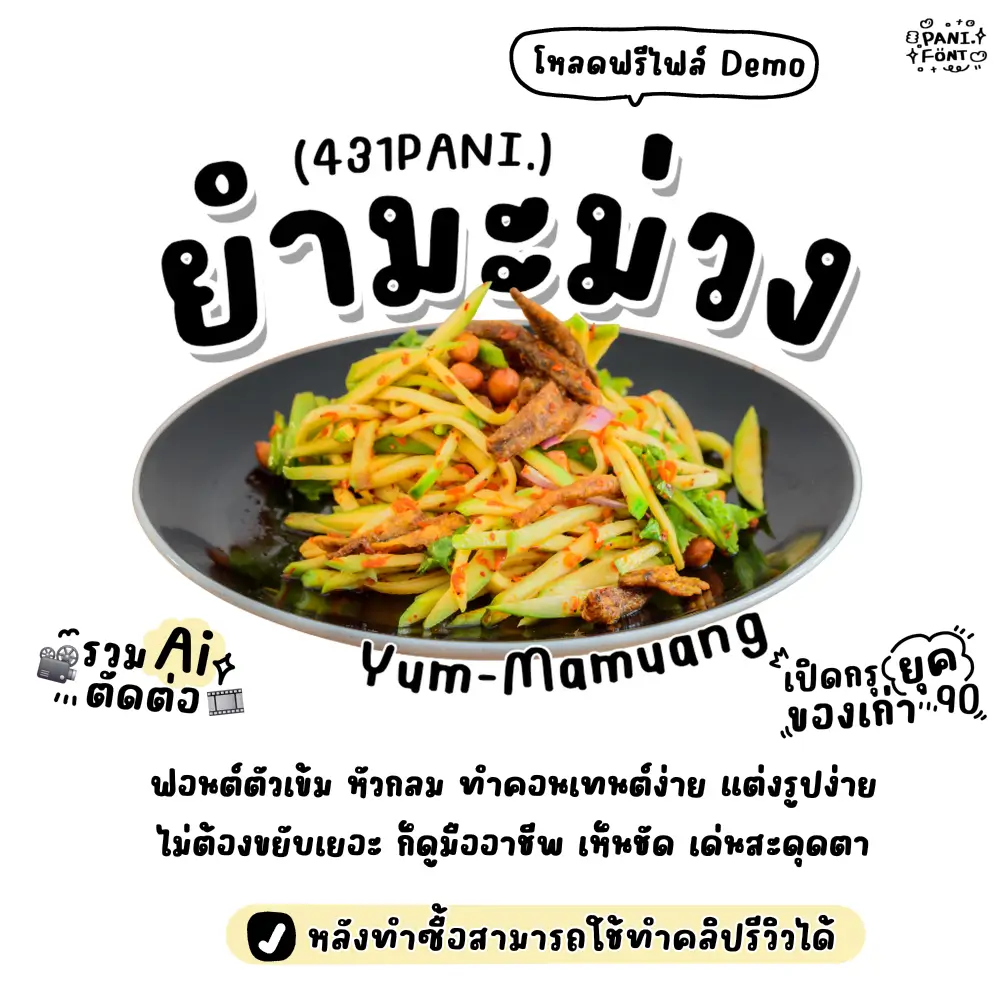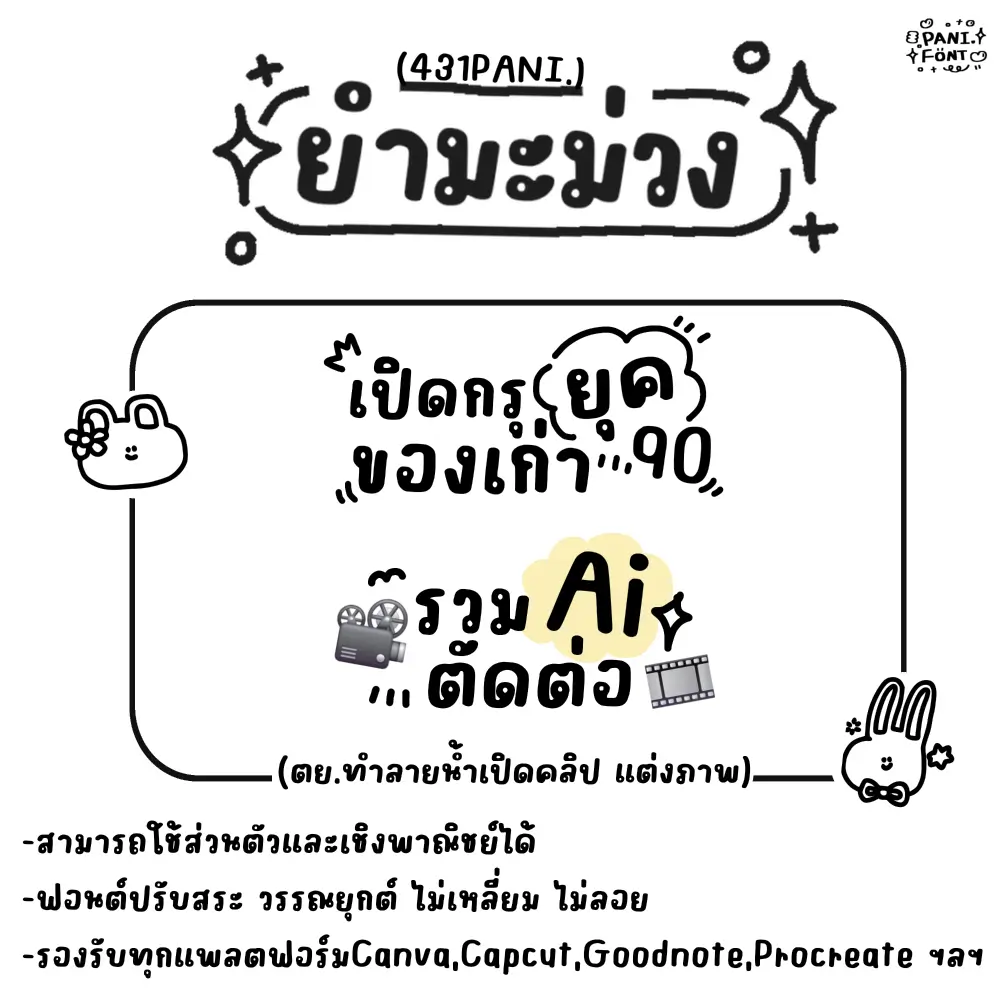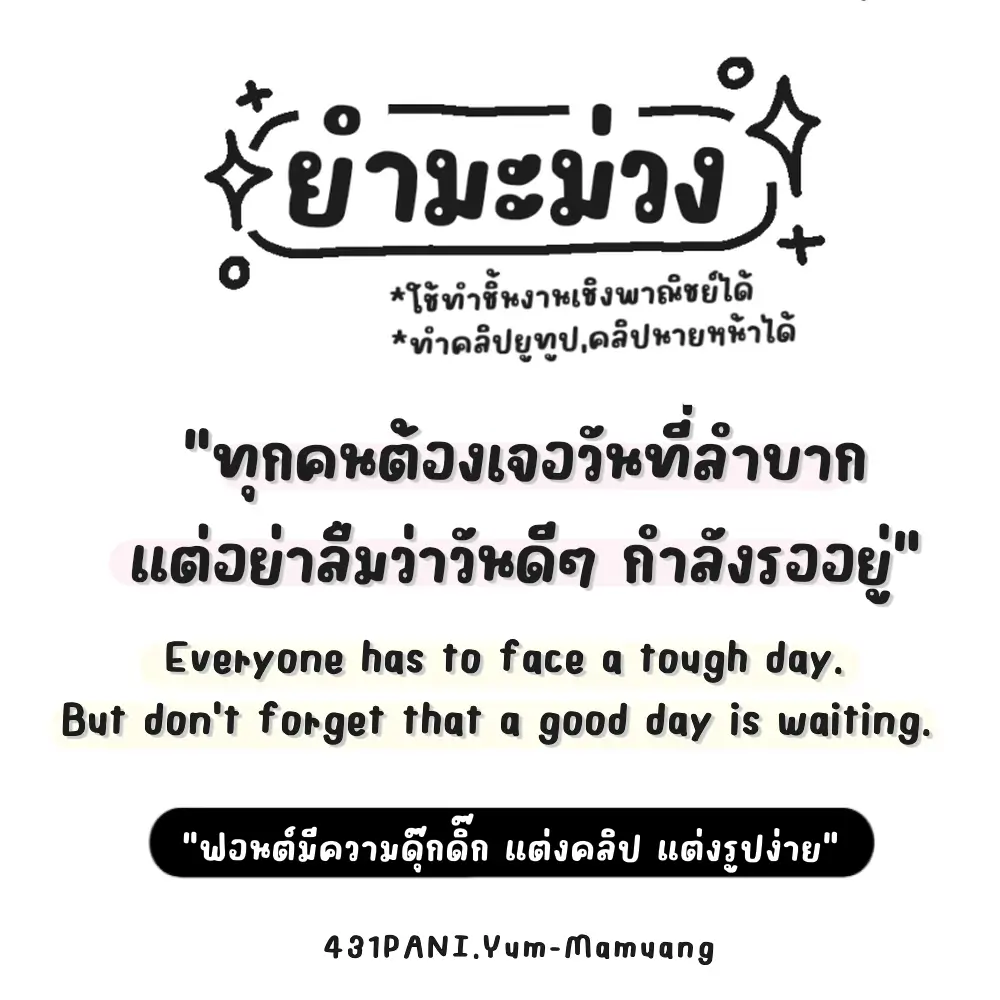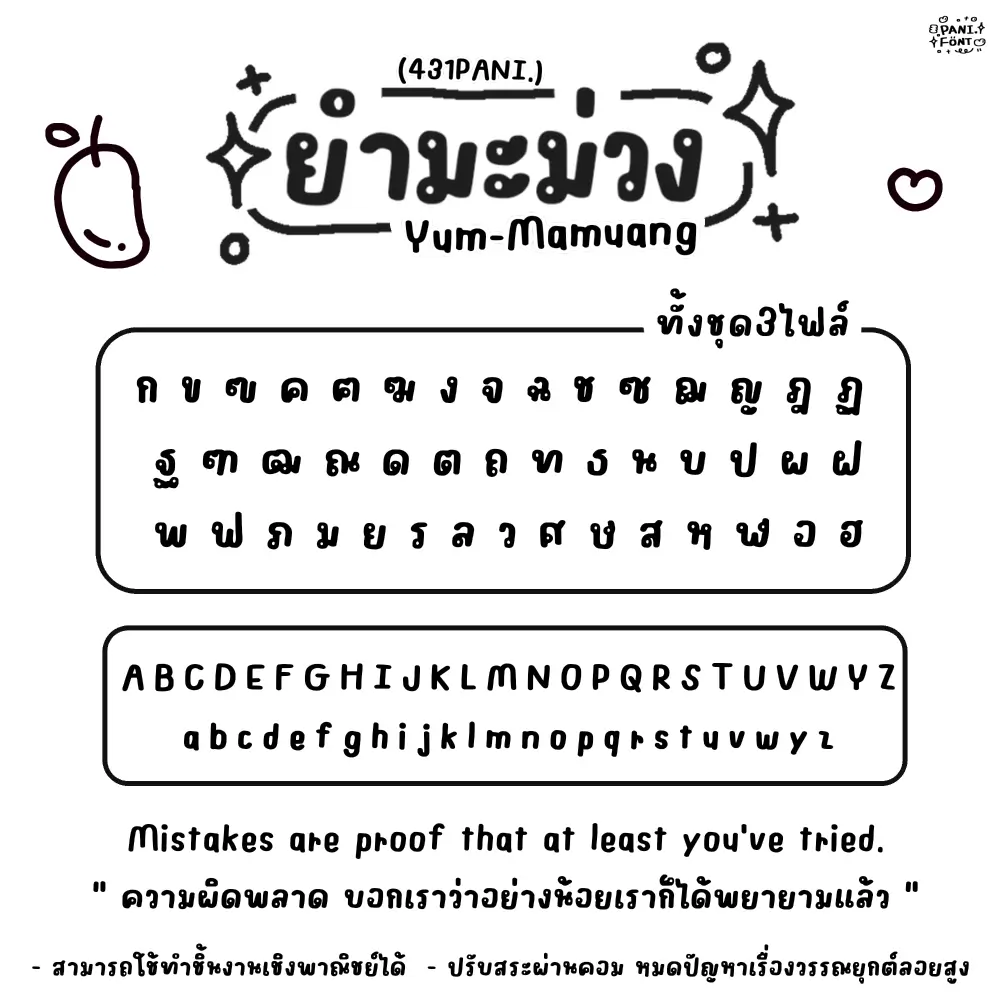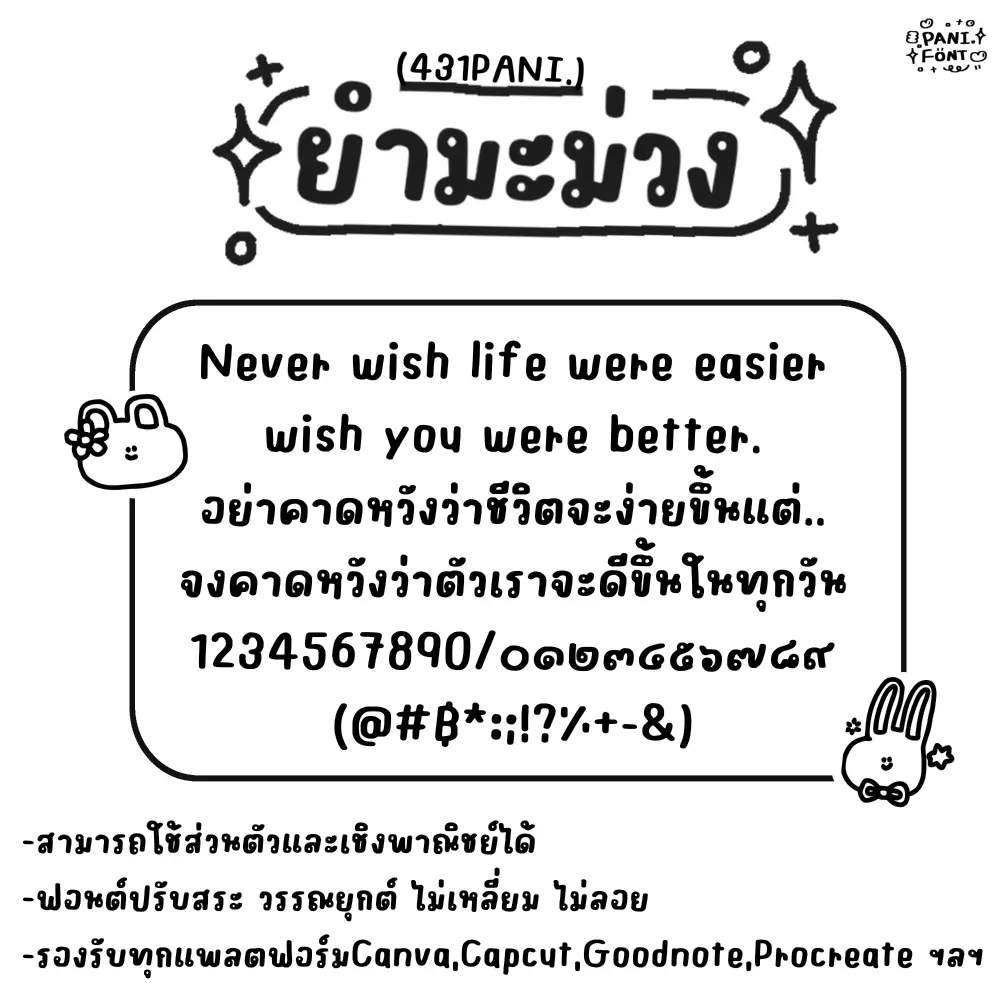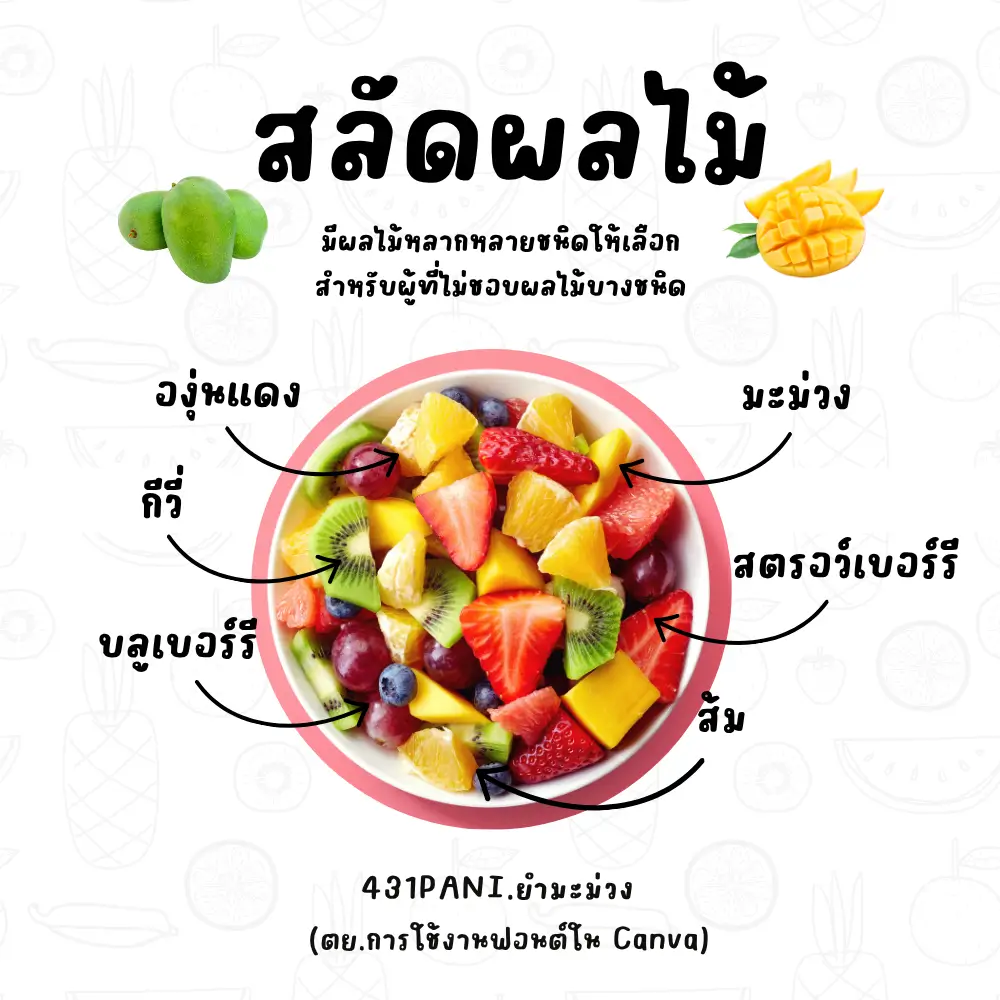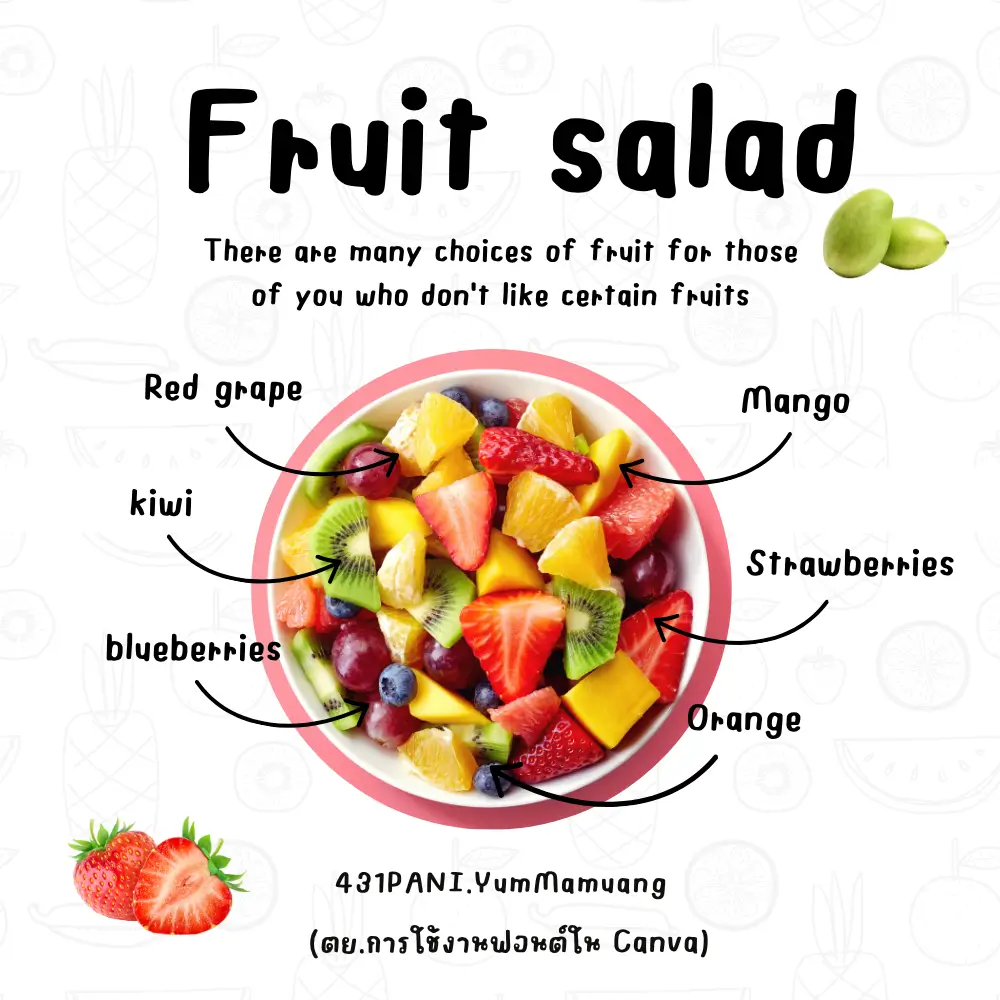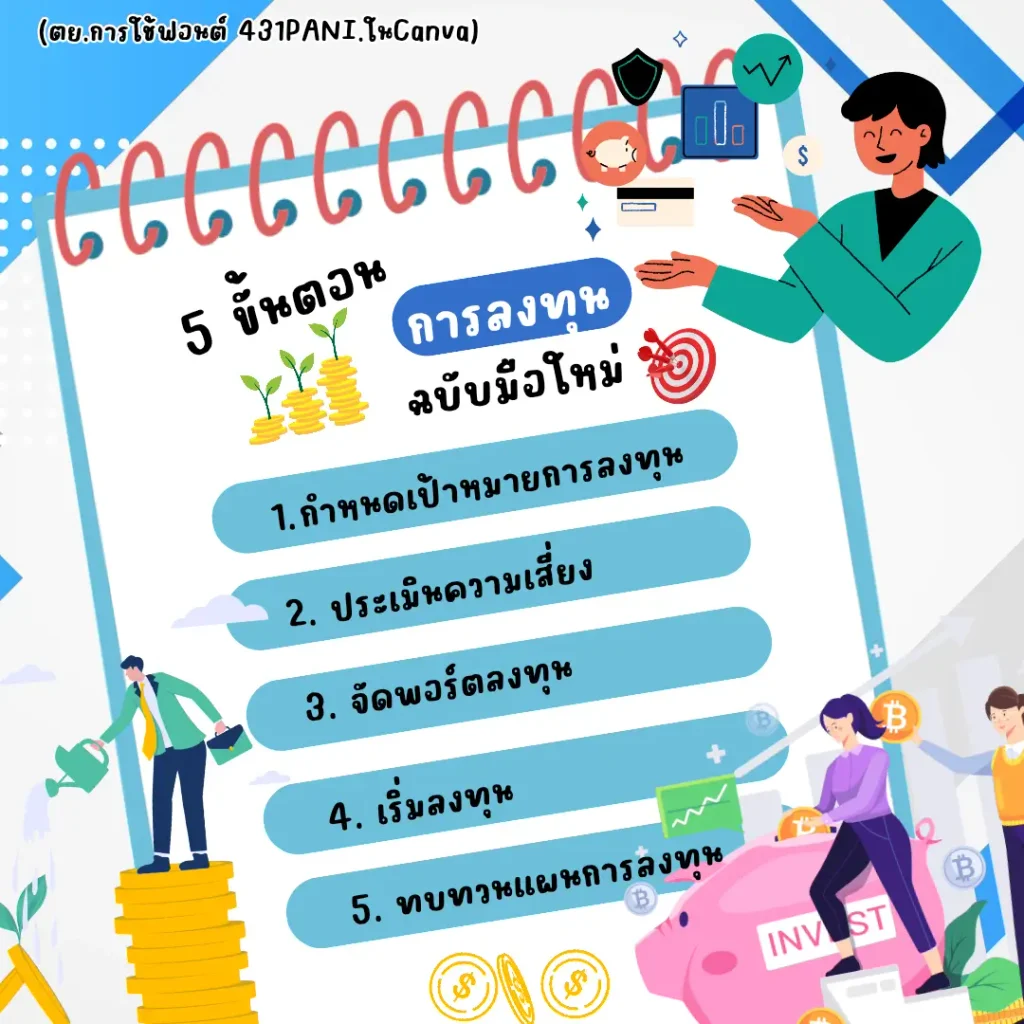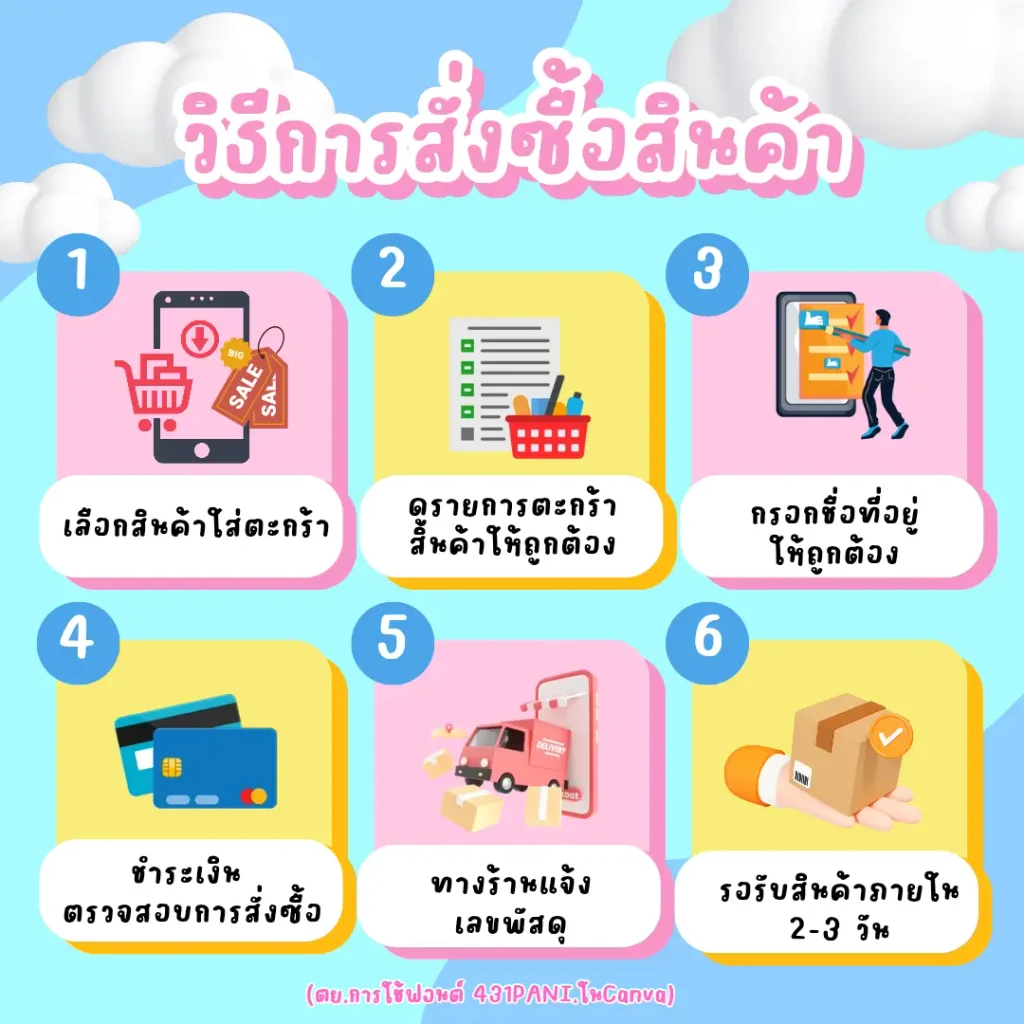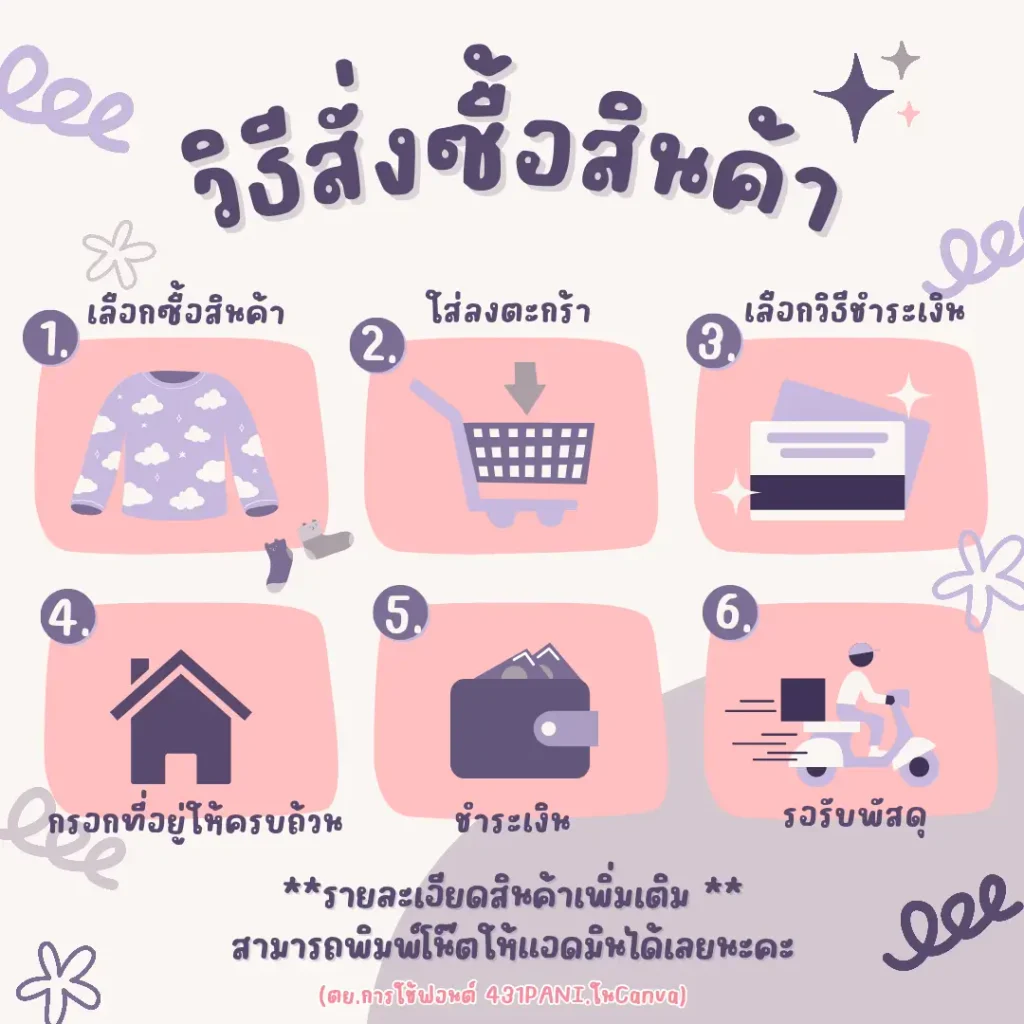
431PANI.ยำมะม่วง (431PANIYumMamuang)
ฟอนต์ 431PANI.ยำมะม่วง – ฟอนต์ตัวเข้ม หัวกลม ใช้งานง่าย มือใหม่ก็ใช้ได้ เด่นสะดุดตา ไม่ต้องขยับเยอะก็สวย เหมือนมืออาชีพ